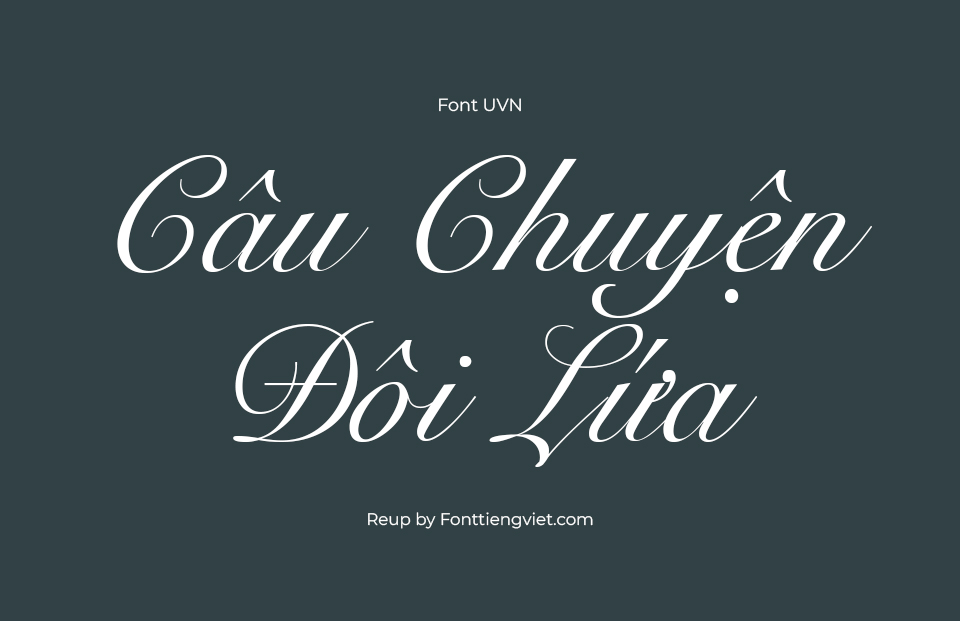
Giới thiệu về Font Việt Hóa UVN Sang Song
Trong thế giới đồ họa hiện đại, việc lựa chọn một Font Chữ phù hợp đóng vai trò then chốt giúp thông điệp truyền tải trở nên ấn tượng hơn. Font Việt Hóa UVN Sang Song là một trong những bộ font tiêu biểu nằm trong dự án UVN nổi tiếng, được thiết kế tối ưu cho bảng mã Unicode. Với đường nét thanh mảnh, rõ ràng và mang đậm nét văn hóa truyền thống, bộ font này đã trở thành lựa chọn hàng đầu cho các thầy cô giáo và học sinh tại Việt Nam khi thực hiện các dự án sáng tạo.
Đặc điểm nổi bật của Font Việt Hóa UVN Sang Song
Thiết kế tinh tế và tính ứng dụng cao
Font Việt Hóa UVN Sang Song sở hữu cấu trúc chữ cân đối, giúp người xem dễ dàng tiếp nhận nội dung mà không gây mỏi mắt. Đây là bộ font lý tưởng để trình bày các bài giảng điện tử, thiết kế báo tường hoặc làm tiêu đề cho các cuốn tập san trường học. Nhờ quy chuẩn Việt hóa hoàn thiện, bạn sẽ không bao giờ gặp phải lỗi hiển thị dấu tiếng Việt, đảm bảo tính thẩm mỹ cao nhất cho văn bản.